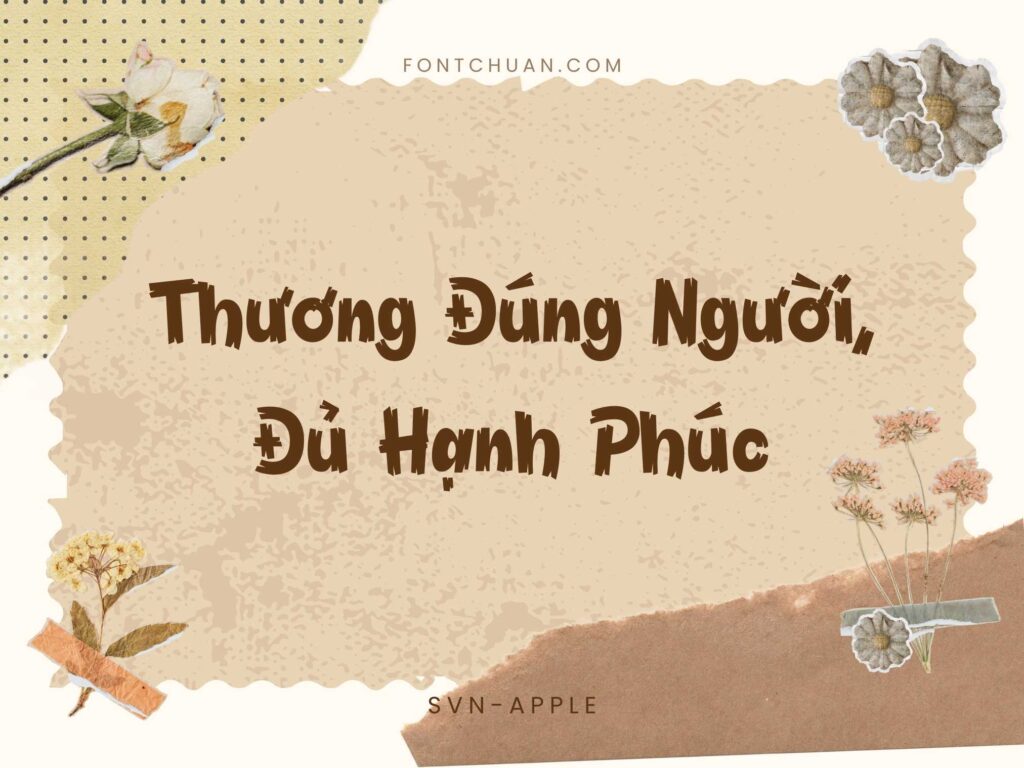
Font SVN Apple Việt Hóa
Apple là một font chữ được Việt hóa bởi Styleno.1 Fonts, mang đến sự lựa chọn mới mẻ cho các nhà thiết kế. Font này hỗ trợ tiếng Việt, giúp người dùng dễ dàng sử dụng trong các dự án thiết kế liên quan đến ngôn ngữ Việt. Font đã được thành viên của Font Chuẩn sưu tầm và chia sẻ, đáp ứng nhu cầu của bạn đọc và ứng dụng thực tế vào các dự án thiết kế.
Đặc điểm thiết kế của font Apple bao gồm các đường nét rõ ràng và hiện đại, tạo cảm giác chuyên nghiệp và thân thiện. Font này phù hợp cho các ứng dụng như thiết kế logo, tiêu đề, ấn phẩm quảng cáo và giao diện người dùng. Các ngành nghề phù hợp bao gồm quảng cáo, công nghệ, giáo dục và truyền thông.